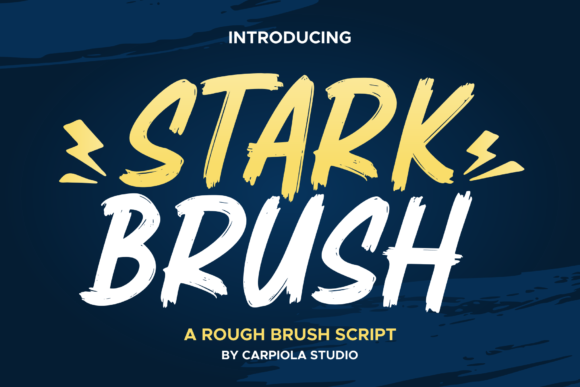
Stark Brush
Encontrar los elementos de diseño adecuados puede ser un desafío, pero Stark Brush ofrece una colección excepcional que eleva tu trabajo al instante.
Ya sea que estés creando productos POD (impresión bajo demanda), invitaciones de boda o gráficos para redes sociales, Stark Brush es una opción ideal.